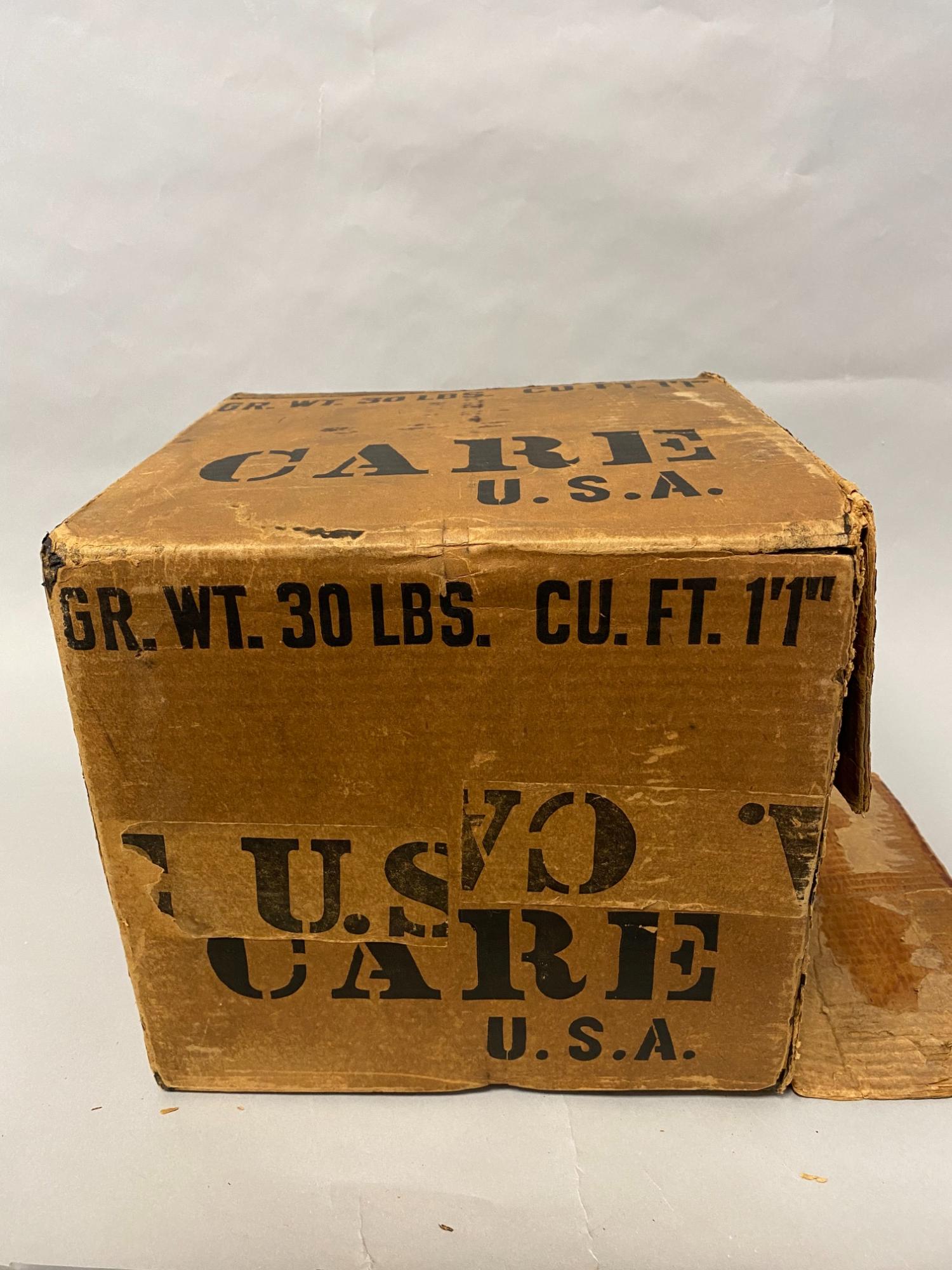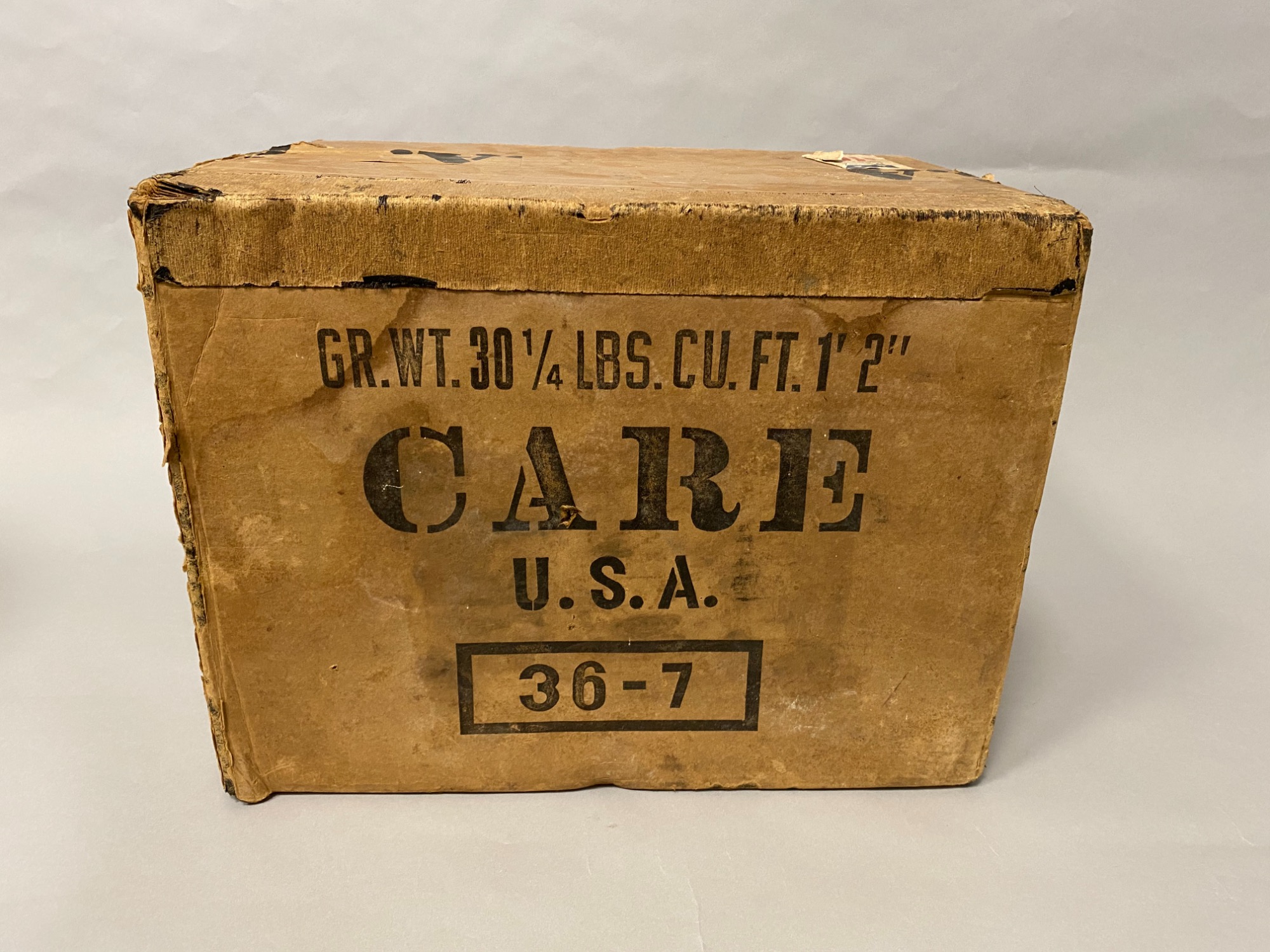
ich bin mal wieder dabei Faksimiles zu gestalten. Auf dem Bild seht ihr verschiedene Schriften, mit denen das Care-Paket bedruckt wurde. Ich suche den Originalen möglichst ähnliche Fonts. Bei der Stencil-Schrift ist die Evidence JNL ziemlich ähnlich oder hat einer noch einen besseren Vorschlag? Das S ist schon sehr anders. Die Serifendose Schrift ist noch schwieriger. Ich schwanke zwischen der Buckwheat TC Regular, Beer Time Base und der Spaceland. Aber so richtig, richtig ähnlich ist keine von denen. Und dann gibt es ja noch den Schriftzug U.S.A. in der anderen Stencil Schrift, aber die kann ich mir selbst zusammenbauen.